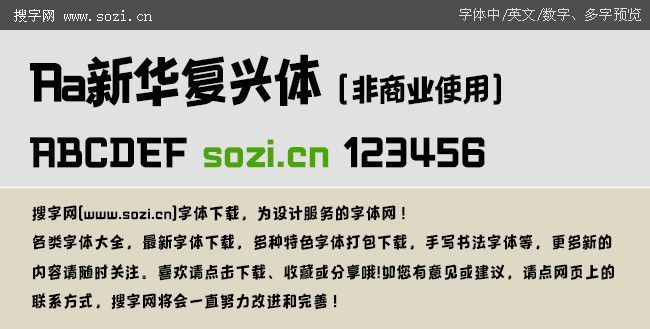
Aa新華復(fù)興體
搜字網(wǎng)給大家提供一款A(yù)a新華復(fù)興體(非商業(yè)使用)中文字體下載,該字體是一款個(gè)性的藝術(shù)字體,字體由黑體字進(jìn)行變化,筆畫(huà)趣味性十足。具有很好的視覺(jué)感,適用于平面宣傳設(shè)計(jì)、網(wǎng)頁(yè)設(shè)計(jì)、海報(bào)設(shè)計(jì)等應(yīng)用(此字體為個(gè)人非商用版,商用可以聯(lián)系QQ:1006760504)。